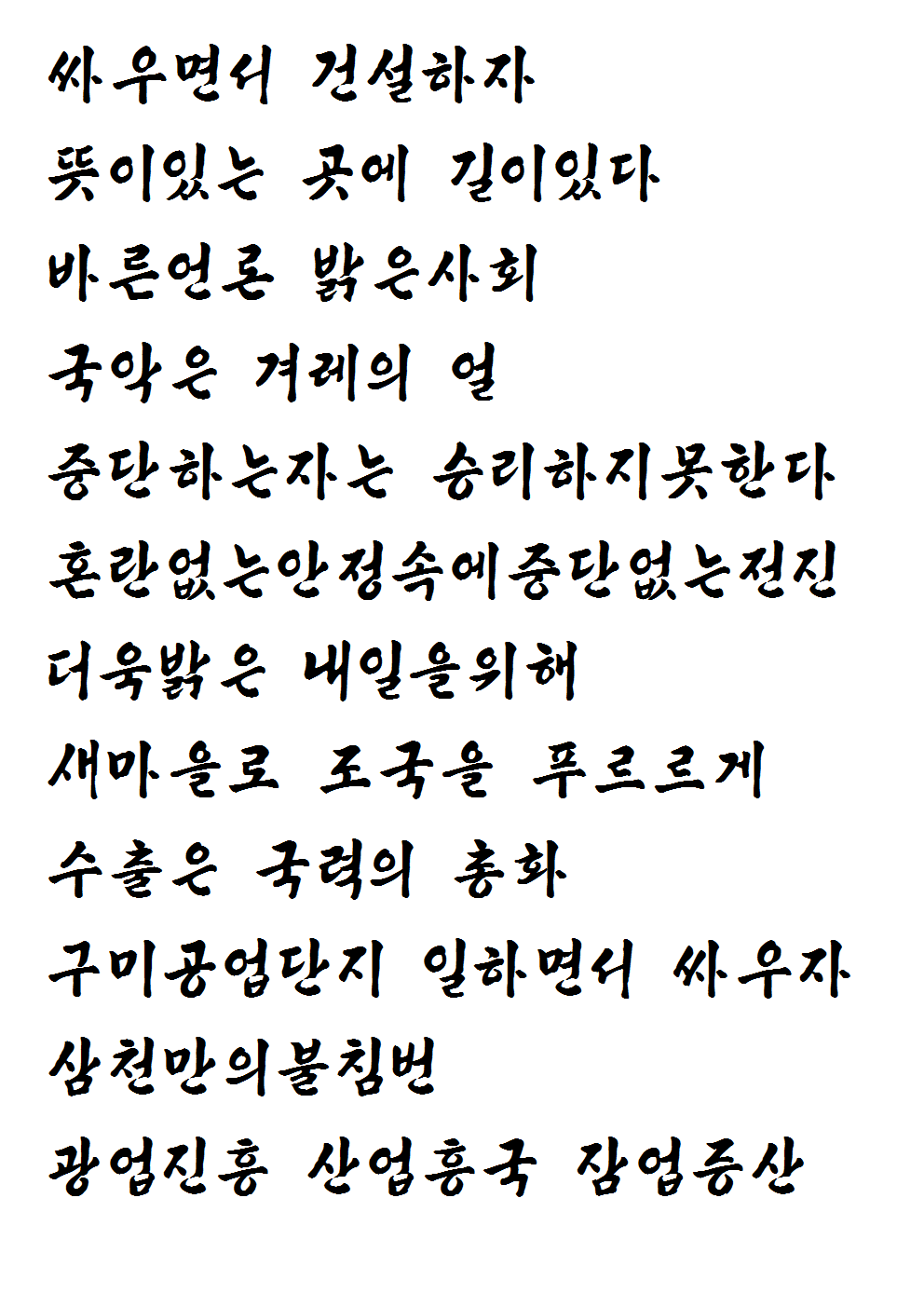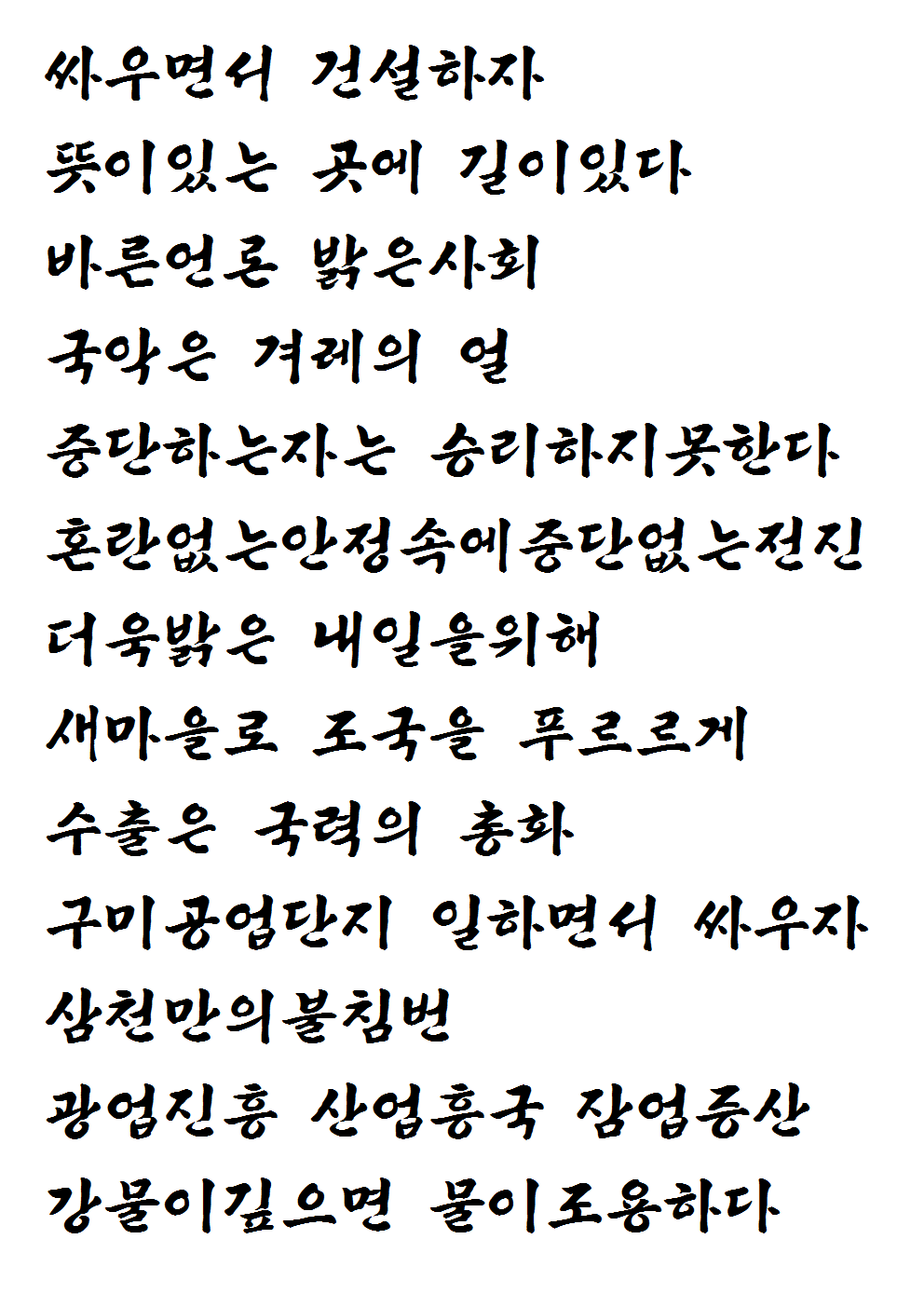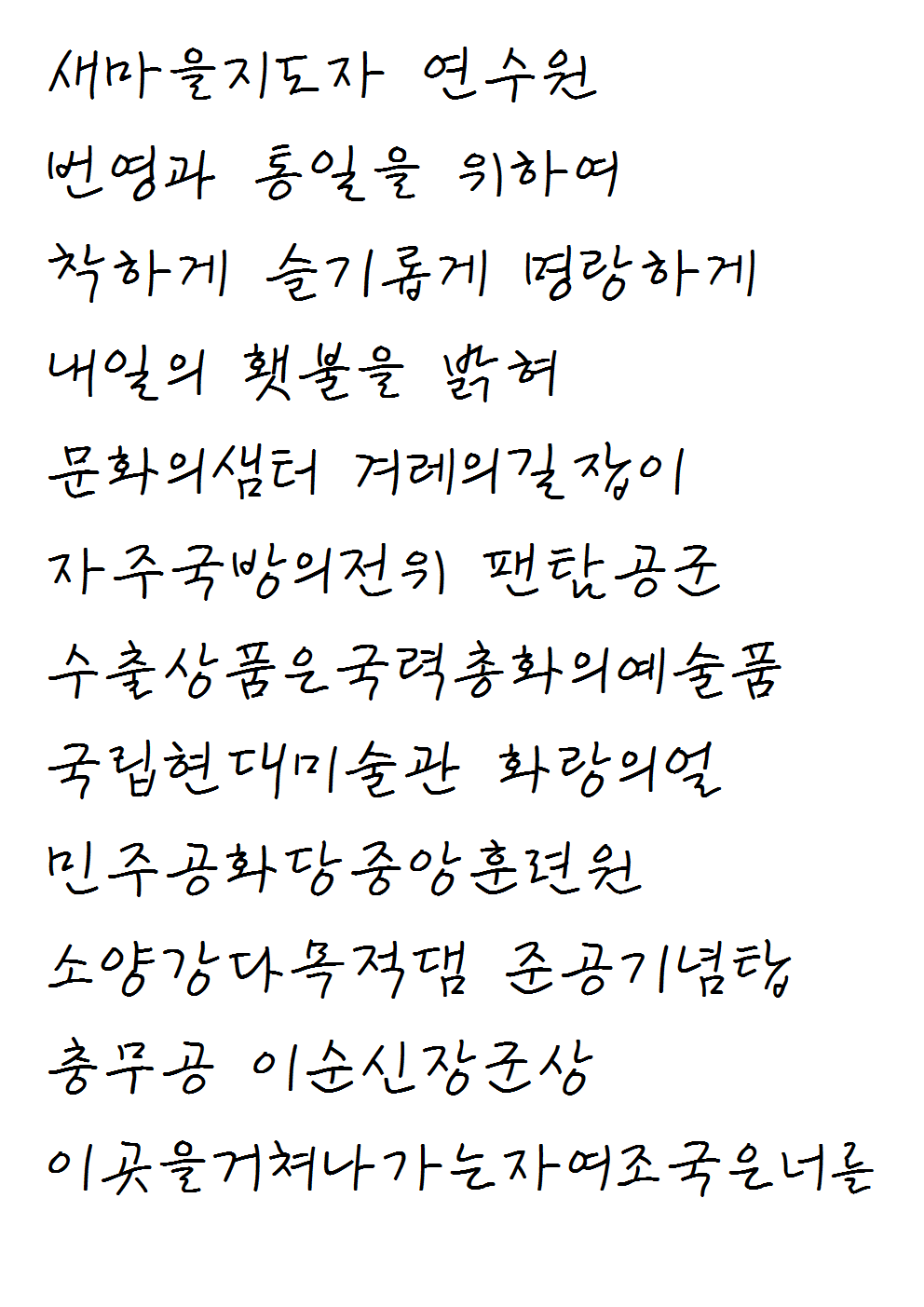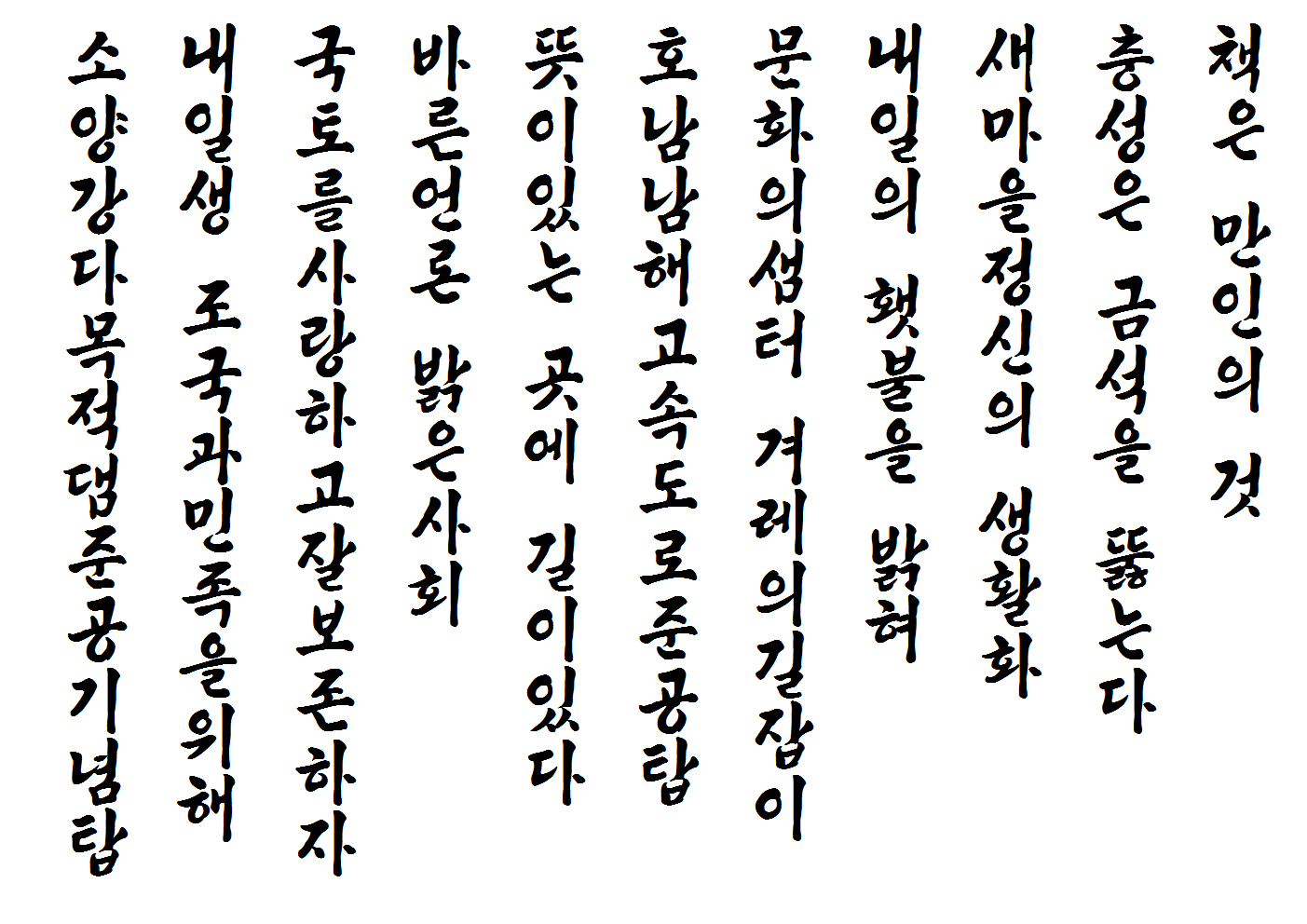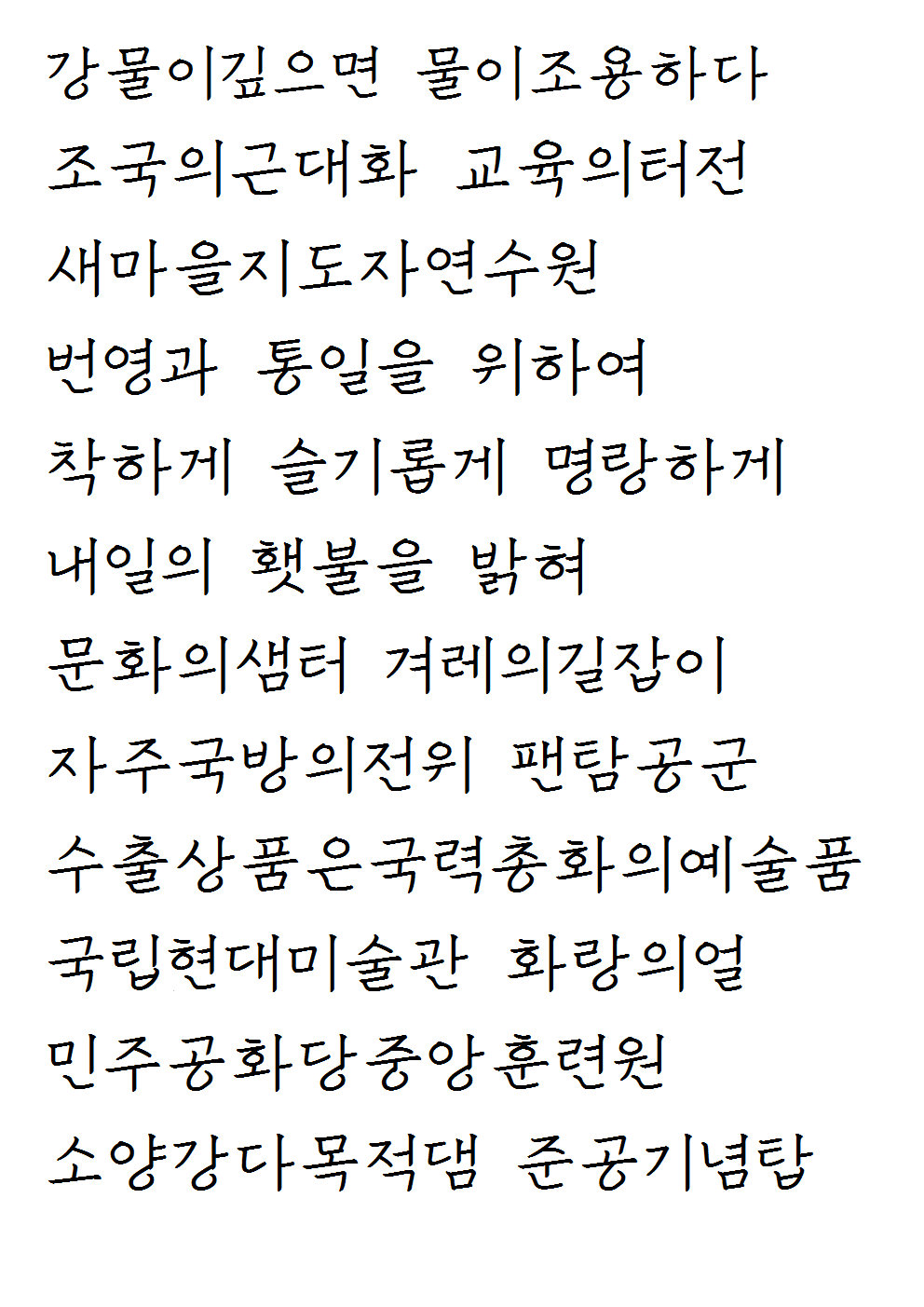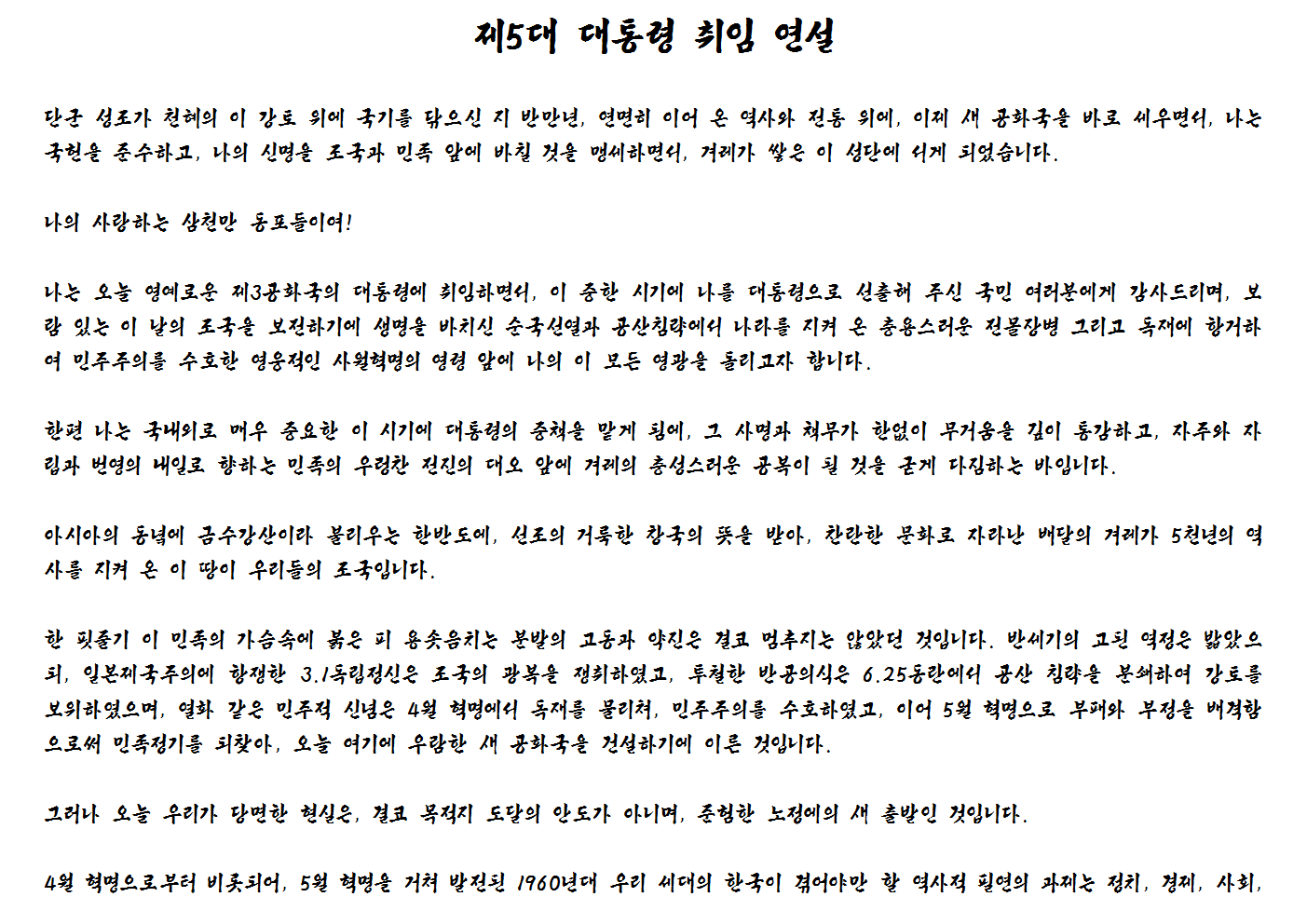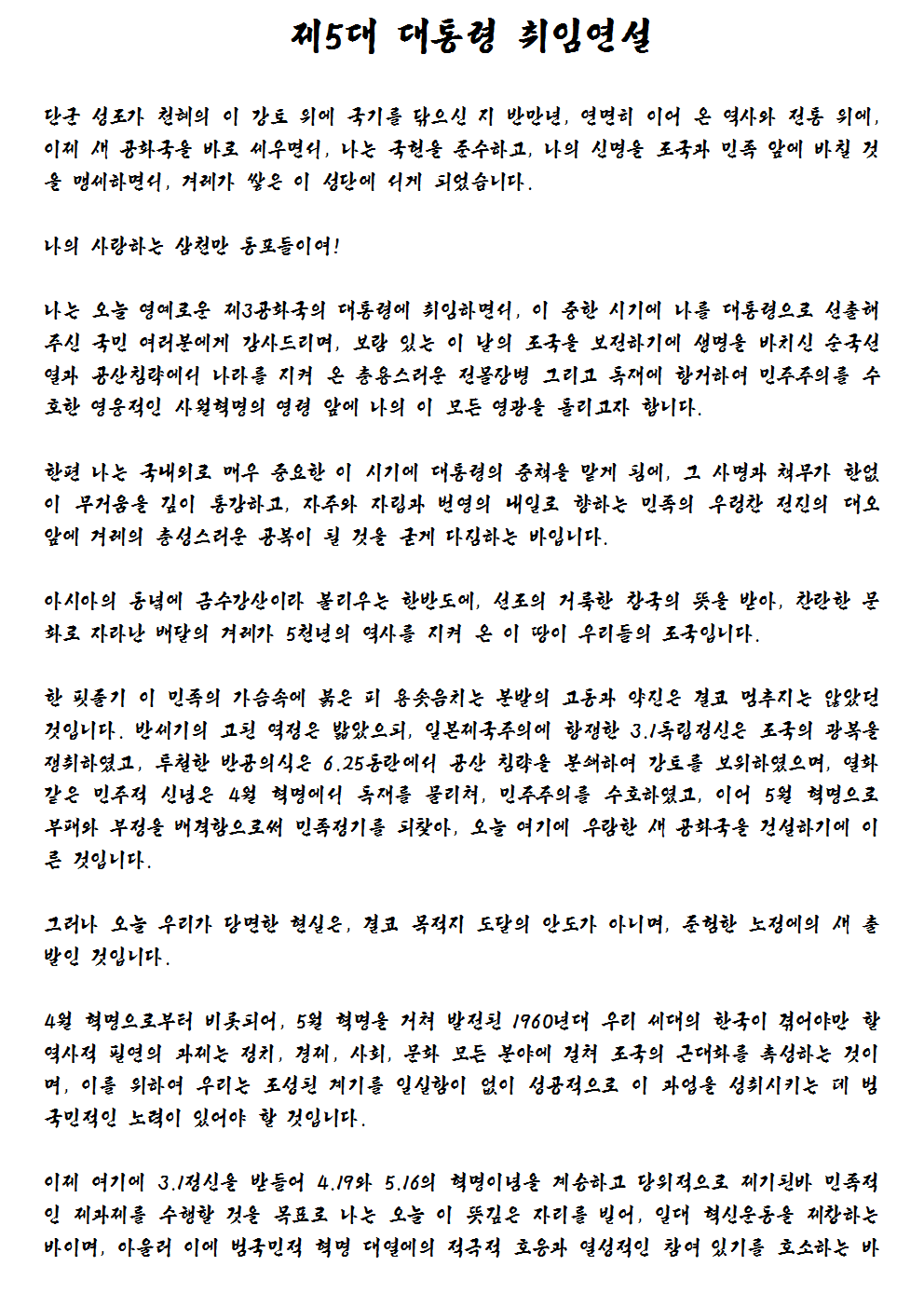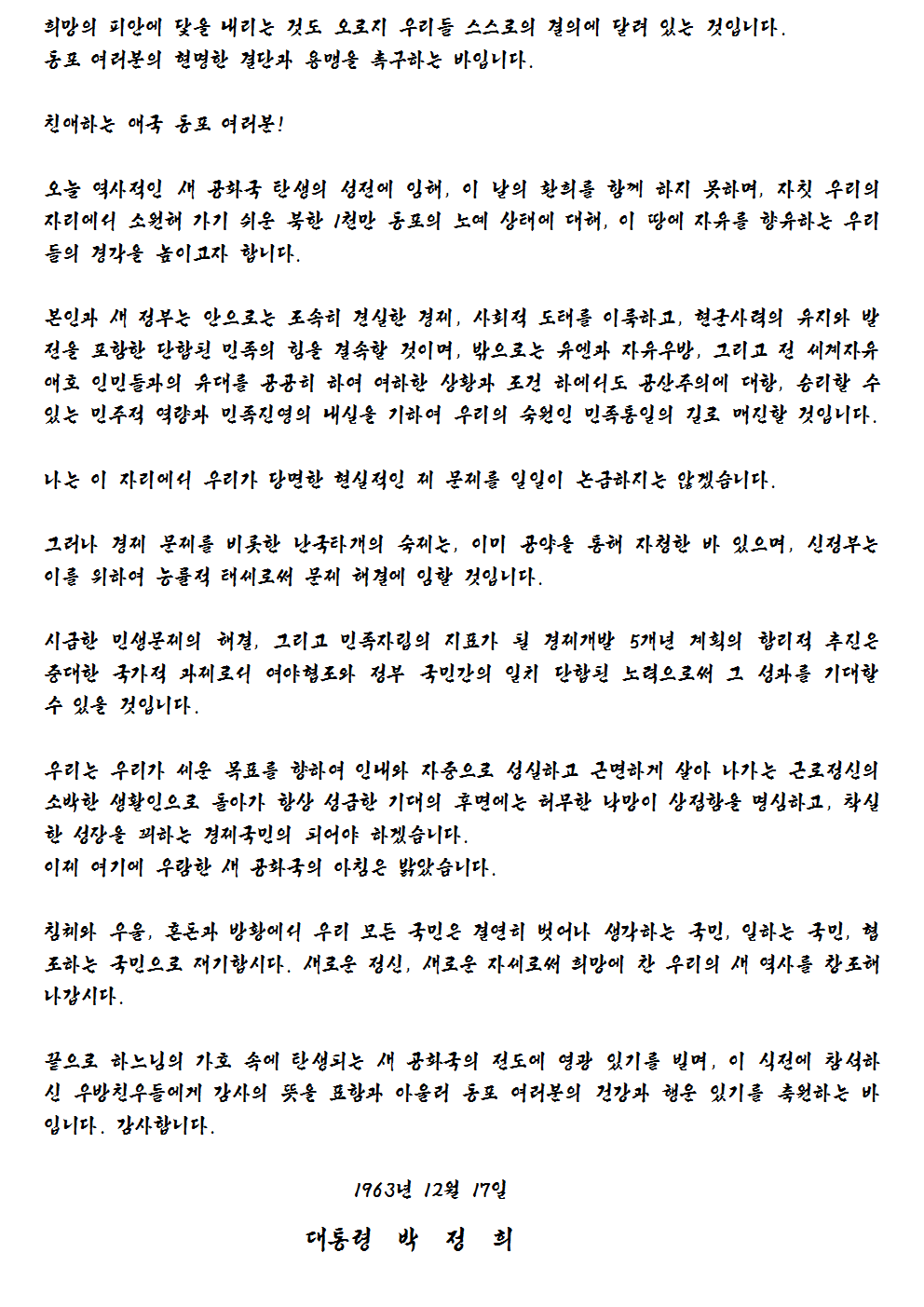
시대의 정신을 서체로 디자인하다
두 명의 대통령 글씨 복원, 국가 프로젝트 공식 디자인, 70년대 간판 글씨체, 가리방 철필 행정체,
그리고 당신의 콘텐츠를 위한 강력한 도구
사용자의 메시지를 가치 있게 만드는 폰트 디자인
왜 ‘김폰트’의 서체여야 하는가?
수만 가지 폰트가 쏟아지는 세상이지만, ‘역사적 서사’와 ‘현대적 감각’이 결합된 서체는 드뭅니다. 저는 10년간 영상의 최전선에서 활동하며, 어떤 글씨가 사람의 마음을 움직이는지 연구해왔습니다.
독보적인 라인업: 박정희서체부터 김폰트 6종까지
현재 박정희서체(한글/한문 예정), 박근혜체, 그리고 옛 간판의 정취를 살린 김폰트서체(옛간판 6종 및 묵향)를 제공하고 있습니다. 각 서체는 단순한 디자인 상품이 아닌, 개발 과정의 치열한 고뇌와 사연을 담고 있습니다.
콘텐츠 창작자를 위한 최적의 선택
– 유튜브 썸네일: 한눈에 들어오는 강렬한 타이포그래피
– 오프라인 행사: 대형 현수막과 기념석에서도 깨지지 않는 완벽한 조형미
– 역사/문화 채널: 콘텐츠의 진정성을 뒷받침하는 고품격 서체
김폰트 그래픽 서체
힘있고 질박한 특유의 붓글씨
국력체L
국력체M
국력체W
국력체P
국력체V
국력체ROK
영상 썸네일에 잘 어울리는 옛간판체
가리방 철필로 쓴 행정체 : 묵향
강력한 텃치의 붓글씨 박정희서체
맑고 단아한 손글씨 박근혜체